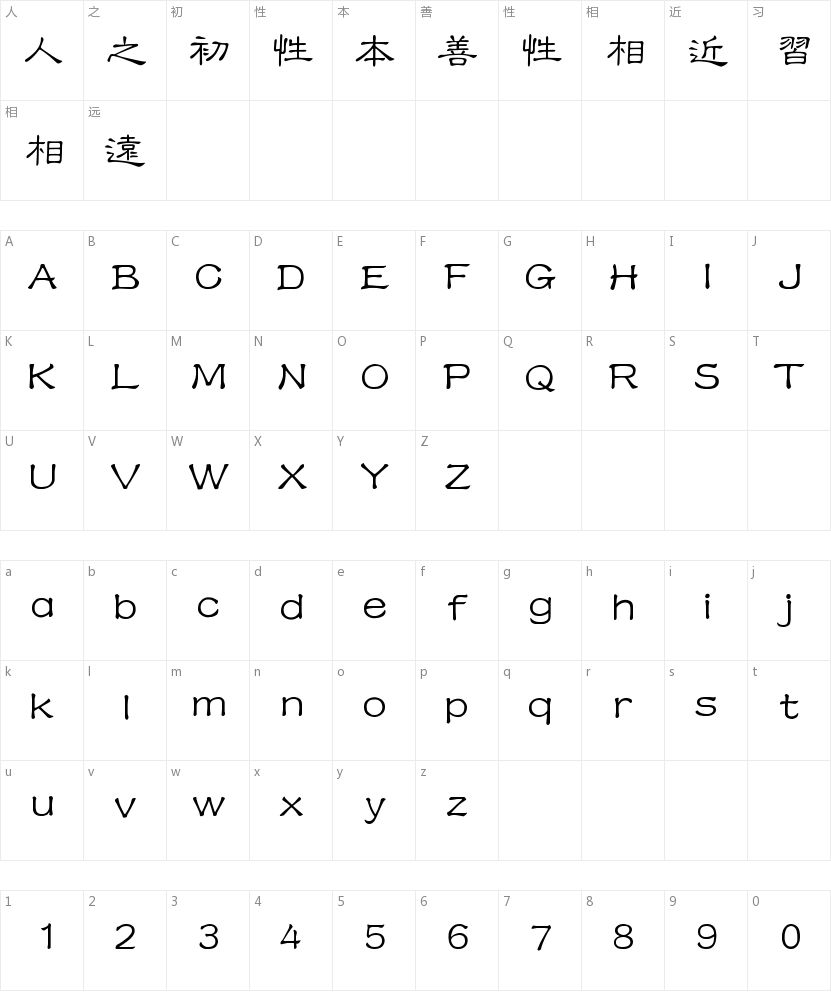
經典細隸書繁,又稱細隸書體,是一種漢字書法體系中的一種書體,最早發源於漢朝,歷代經歷了多次演變,形成了今日的經典細隸書繁。其特點是字體細小,筆劃細膩,筆勢靈動,結構簡潔,表現出一種清新、柔和的美感。它的字形曲折細膩,筆劃細膩,筆勢優美,結構簡潔,筆劃間的關係恰到好處,構成了一種清新、柔和的美感。內容介紹
經典細隸書繁是一款非常不錯的手寫藝術字體,具有很好的視覺感,適合於文化類的宣傳設計、商業類品牌的廣告和產品包裝設計以及個性化文字排版等較多場景。